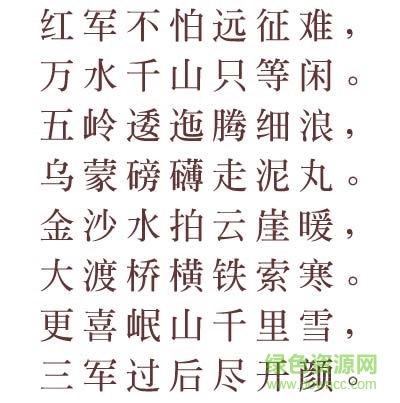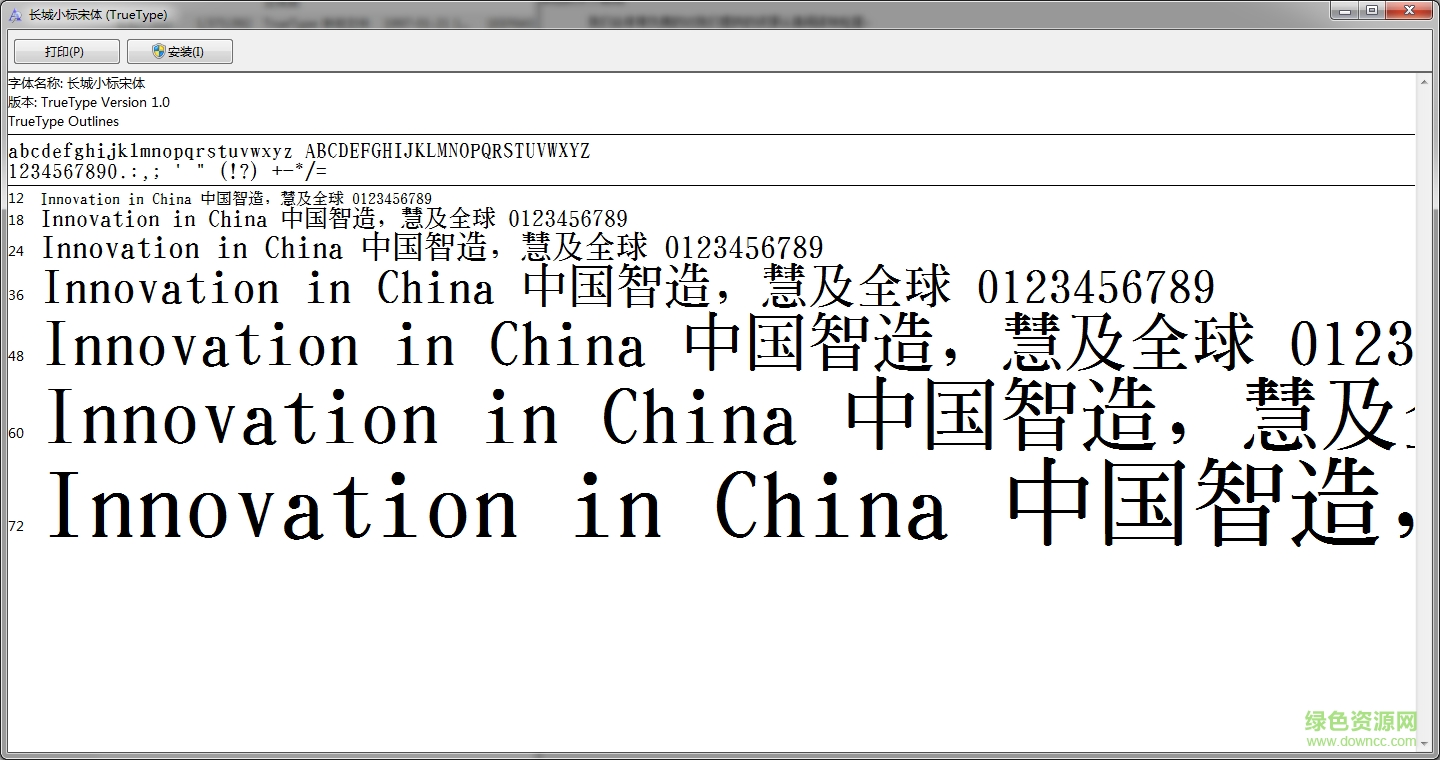
長城小標宋體字體是長城字體庫中很常用的宋體字體,字形清晰明目。綠色資源網(wǎng)帶來的為ttf格式,喜歡的朋友,趕快下載體驗吧!
1.中國的字體設計是在印刷術的產(chǎn)生和發(fā)展中應運而生的。在古代,中國的字體設計曾有過輝煌的歷史時期,在宋朝時進入黃金時代。
2.清朝末年,鉛字排版印刷術傳入中國,字體設計進入鉛字時代。這個時期的字體設計既要帶有傳統(tǒng)文化的審美慣性,又要符合鉛字印刷的工藝要求,字體設計走到了轉(zhuǎn)折的關口。
3.鉛字印刷是印刷走入機械化、工業(yè)化時代的標志,但在這一時代里,印刷字體設計卻始終無法超越手工勞動的制約,無法擺脫刻模、鑄字、撿字、排版等一系列印前繁雜工藝的束縛